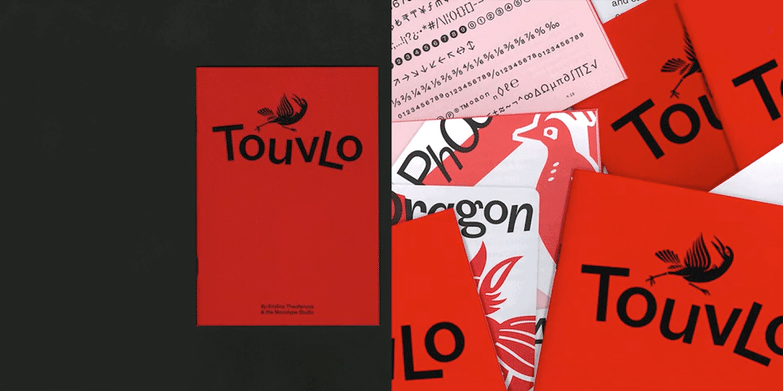
Quatro dicas para ser mais sustentável ao criar.
“ Colocar o design sustentável em prática não é fácil. A mudança demanda tempo e esforços de longo prazo para que se cause um impacto. ”
Touvlo Specimen GIF
Quando se fala de criar uma marca sustentável, o sucesso é questão de um único elemento: autenticidade. Promover sua marca como sustentável é uma coisa, mas praticar o que se prega é onde o sapato aperta e os clientes sabem a diferença.
Pense no fundador da Patagonia, Yvon Chouinard, que há pouco doou a empresa de vestuário, avaliada em US$3 bilhões, para uma organização ambiental sem fins lucrativos para ajudar a combater a mudança climática. Trata-se de uma mudança que ganha o respeito dos clientes, ao contrário de compensação de carbono, reconhecida por eles como um golpe de publicidade.
Nos últimos cinco anos, houve um aumento de 71% nas pesquisas online por produtos sustentáveis a nível mundial, e 66% dos consumidores que participaram da pesquisa levam a sustentabilidade em consideração ao fazer uma compra. O lucro, atualmente, está ligado intrinsicamente à sustentabilidade.
Se você trabalha para uma marca que valoriza a sustentabilidade, como contar essa história por meio do design? Independentemente de trabalhar para uma empresa certificada B Corporation ou uma marca que acaba de começar sua jornada sustentável, temos aqui quatro maneiras de ser mais sustentável ao criar:
1. Tenha um diálogo transparente com a marca acerca da pegada de carbono de seus designs
Frequentemente as marcas têm boas intenções, mas não sabem como colocá-las em prática. No papel de designer, você pode educar marcas a respeito de seu impacto ao propor soluções de design com uma pegada de carbono mínima. Por exemplo, de forma a reduzir o material usado, é possível fazer malas diretas que funcionam como envelopes dobráveis ou deixar uma borda branca no entorno de cartazes para reduzir o desperdício de tinta nas sangrias.
Por mais que marcas possam ter uma política interna em que doam uma porcentagem de seus lucros para organizações de caridade ou optem por plantar árvores para substituir os produtos de papel que utilizam, a mudança verdadeira começa com práticas de longo prazo. Marcas podem estabelecer um código de conduta para desenvolvimento da sustentabilidade a nível de cadeia de suprimentos. Há muitos recursos a serem consultados pelas marcas, como os 10 Princípios do Pacto Global da ONU e os padrões delineados pela Organização Internacional do Trabalho.
2. Minimize o impacto ambiental da marca por meio de embalagens sustentáveis.
Caso esteja criando para uma marca que fabrica produtos físicos, pode encorajá-la a minimizar o desperdício de papel através de práticas de maximizar a página toda ao imprimir e incorporar fontes que economizam tinta, fontes especializadas que exigem menos tinta para serem impressas. Sendo assim, qual a melhor fonte sustentável para economizar tinta? Times New Roman, Ryman Eco e Century Gothic são todas consideradas fontes ecológicas para impressão por conta de suas linhas finas, que minimizam o volume de tinta necessário. A Ryman Eco é uma alternativa particularmente distinta porque usa 33% menos tinta que fontes comuns. Outro bom exemplo de como fontes podem reduzir custos se dá com a Garamond, por conta de seus traços mais finos, ela pode reduzir o uso de tinta em até 24%, gerando uma economia estimada de US$21.000 ao ano para um distrito escolar.
Também é possível encorajar marcas a aplicarem design sustentável em suas embalagens para envio. Optar por um pacote reutilizável ou feito de papel reciclável para processamento facilitado. É importante se certificar de que os materiais usados possam ser reciclados com facilidade, já que 67% dos consumidores consideram importante que os produtos que eles compram venham em embalagens recicláveis.
3. Estimule o design digital sustentável através de fontes comprimidas.
De forma a sermos mais amigáveis para com o ambiente, podemos começar a pensar em oportunidades para fazer de nosso mundo digital mais sustentável. A internet usa 1 bilhão de toneladas de gases do efeito estufa ao ano e é responsável por 2% das emissões globais (uma pegada de carbono maior que a da indústria da aviação), então mesmo pequenos passos para estimular um design digital sustentável já caminham para a direção certa. Enquanto designer, você aprimorar seu design digital ao usar fontes sustentáveis incluindo fontes comprimidas, fontes variáveis e microfontes.
Por que usar fontes comprimidas? Elas carregam mais rápido, o que acelera a velocidade de carregamento de sites também. Isso não só é mais ecológico, como essencial para reter seus clientes; a probabilidade de rejeição aumenta 123% caso o tempo para carregar uma página móvel aumente para 10 segundos. Também é possível optar por fontes variáveis para agilizar o carregamento da página. Bastará baixar um arquivo de fonte e você terá acesso a milhares de combinações de pesos e estilos. De fato, comprimir imagens e texto em apenas 25% das páginas poderia economizar mais de 250KB e 10% poderia economizar mais de 1MB.
Também é possível usar um “tipo micro” fonte geralmente abaixo dos 10 pontos de tamanho a ser aplicada em ambientes como rotulagem de embalagens, e-books ou smart watches. Caso opte por um tipo micro, certifique-se otimizar suas configurações para melhorar a legibilidade. O maior benefício de ter um tipo micro altamente legível é que isso possibilita uma maior confiança na mudança para o digital. Para encontrar um tipo micro que funcione para você, busque em um portal de fontes.
Ao pensar em um design focado no bem, reconheça o papel desempenhado por você. Como designer, você tem a oportunidade para ajudar a educar marcas por meio de diálogos de impacto positivo ao receber o briefing de um projeto. Você tem o poder de fazer do mundo um lugar melhor através de suas práticas de design.